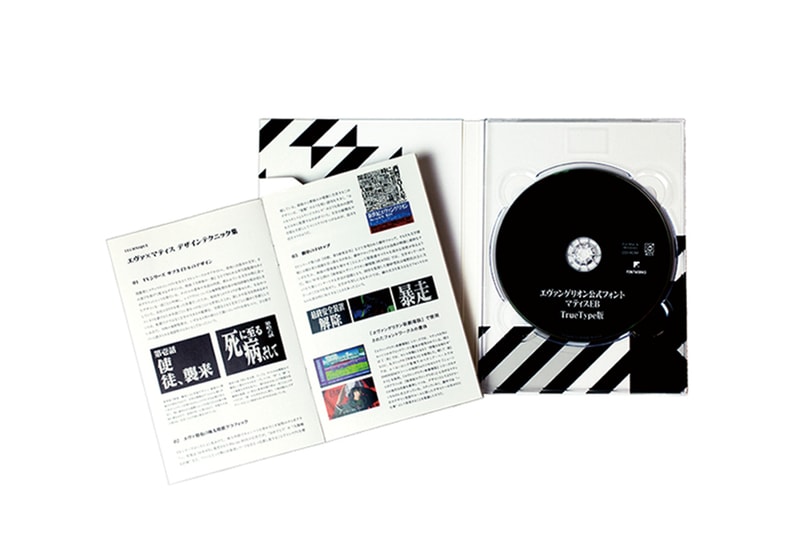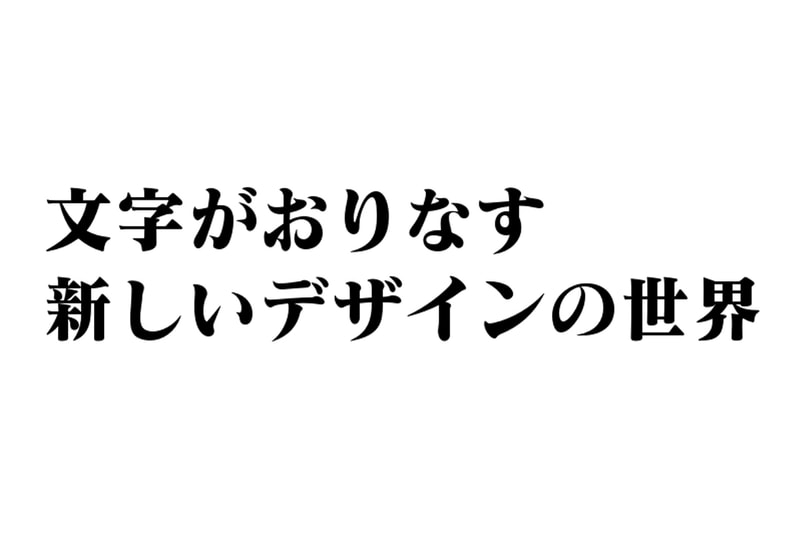
《新世紀福音戰士》文字何價?
填上什麼文字好呢?
文字未必值錢,但特別字體就越來越受歡迎,早前有香港設計師 Kit Man 發起眾籌計劃支持其所創作的字體「勁揪體」成功籌得 65 萬,那邊廂日本動畫《新世紀福音戰士》也要出售其官方字體了。自 1995 年開播以後,《新世紀福音戰士》就以獨有的原創黑底白字(或白底黑字)方式作為過場,而現在官方網站就準備於 11 月初出售當中所使用的字體「新世紀福音戰士公式(官方)字體 Matisse EB」。字體共分有個人版及商業版兩種類,如果要用該字體作商業用途就必需買商業版了。